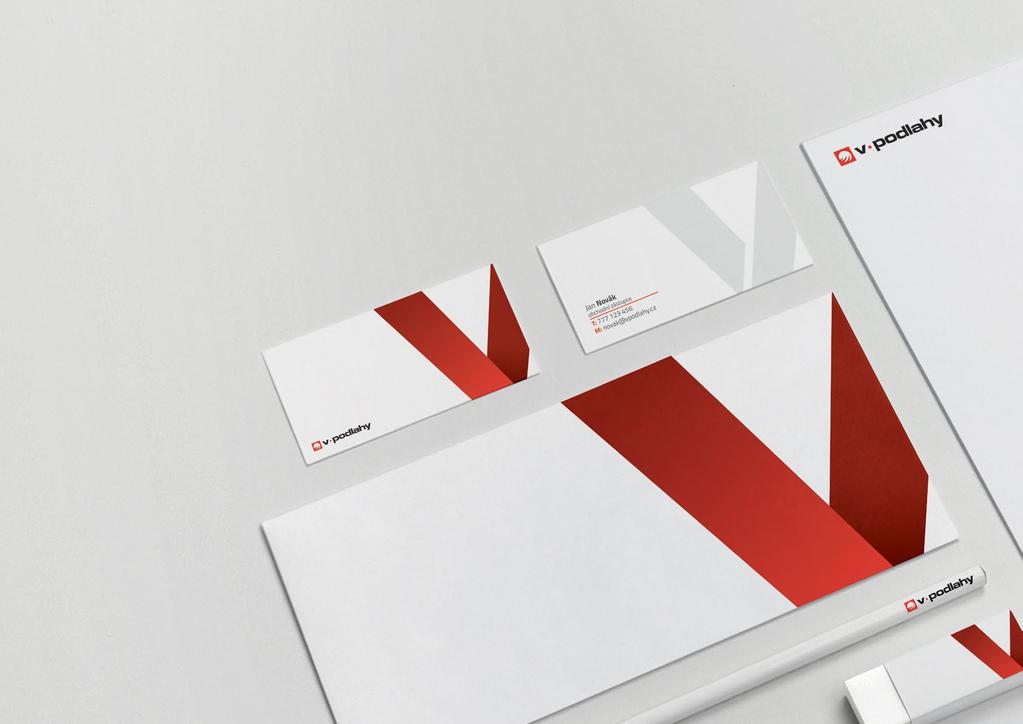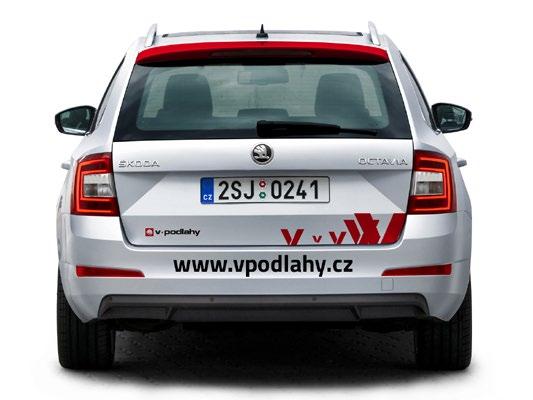
VIZUÁLNÍ STYL. Jednotícími prvky vizuálního stylu značky V-podlahy je ikona z loga, typografie, barevnost a pruhovanost.
3 VIZUÁLNÍ STYL Jednotícími prvky vizuálního stylu značky V-podlahy je ikona z loga, typografie, barevnost a pruhovanost. Cílem vizuálního stylu je působit sjednoceně. Vytvořit u cílové skupiny myslovou vazbu na jednotící prvky, které si jednoduše spojí s názvem V-PODLAHY. Vizuální styl má vyjadřovat moderní a svěží přístup. Výběr financí a sdružování kreativců do komunity. Schopnost pomáhat projektům nejen výběrem financí. Vždy je nutné dodržovat všechny jednotící prvky a řídit se předpisy pro vizuální komunikaci, kterou tento manuál sepisuje, aby se značka dala snáz cílovou skupinou zapamatovat. 3
7 ÚVODNÍ SLOVO A SPECIFIKACE ZNAČKY Corporate design manuál společnosti V-PODLAHY, s.r.o. je základním prostředkem k vytvoření jednotného vizuálního stylu, který společnost profiluje a dostává ji do podvědomí klientům, obchodním partnerům a široké veřejnosti. Jedná se o plnohodnotný marketingový nástroj a je jedním z prostředků k dosažení strategických cílů společnosti. Je také nástrojem, který odlišuje od konkurence. Jednotný vizuální styl je vytvořen z názvu společnosti, logotypu, firemního písma a firemní barvy. Pro vytvoření jednotného vizuálního stylu je nutné řídit se pravidly pro používání těchto základních prostředků ve všech formách vnější i vnitřní komunikace společnosti. Působení firemního stylu není omezeno navenek, ale významným způsobem ovlivňuje i vnitřní chod společnosti. Doporučení či nařízení pro správné užívání logotypů Podobu a pravidla použití jednotného vizuálního stylu popisuje tento grafický manuál, který je nezaměnitelný, originálním a závazným návodem k používání. Grafický manuál je především návodem k používání prostředků jednotného vizuálního stylu pro následnou realizaci. Jeho přesné dodržování je ve vlastním zájmu společnosti. Je zakázáno používat samotný logotyp nebo název společnosti bez respektovaní jednotného vizuálního stylu společnosti. V tomto manuálu jsou uvedeny příklady zakázaných variant, které však nevyčerpávají všechny zakázané způsoby použití. Jsou zakázány rovněž všechny způsoby použití, které se odlišují od variant povolených a popsaných v tomto manuálu. Pro jakékoliv způsoby použití je nutno respektovat pravidla tohoto grafického manuálu tak, aby nebylo poškozeno dobré jméno společnosti V-PODLAHY, s.r.o. 7
9 Logotyp Základní varianta logotypu se používá jako název s ikonou vodorovně. Varianty logotypu Vodorovná varianta Svislá varianta Samotný piktogram lze použít jako značku. Manuál zakazuje deformaci logotypu, změnu barevnosti, přidávání efektů, natáčení do jiných poloh než horizontální, změnu písma a změnu poměrů velikostí. 9
11 ochranná zóna Do místa ochranné zóny nesmí přijít žádný prvek, který by narušoval čistotu logotypu. Ochranná zóna je definována výškou piktogramu. Nejmenší velikosti se využívají hlavně na potisky propagačních předmětů, tiskovin apod. Minimální velikosti neplatí pro použití v digitální distribuci (web). ochranná zóna Ochranná zóna je zejména užitečná na prostoru, kde se logo V-PODLAHY nachází vedle dalších společností. Důležitá je výborná čitelnost a nenarušování ostatních logotypů. Ochranné pásmo kodifikuje piktogram. Určuje tak vzdálenost od stran bílého vnitřního obdélníku. 10mm Nejmenší šířka samotné ikony je 10 mm. 57mm Nejmenší šířka samotného nápisu je 57 mm. Nejmenší šířka horizontální varianty názvu s ikonou je 69 mm. 11
13 Logotyp se používá buď na bílé (až velice světlé) podkladové ploše v červeno-černé variantě, nebo na čistě červeném podkladu v bílé variantě. Podklady není možné měnit. Na fotce a odlišných podkladových plochách (např. video) se může použít buď pouze název a nebo logo skládající se čistě z bílé barvy. Bílé anebo velice světlé pozadí. Maximálně do 10% šedi. 13
15 DEFINICE BAREV Pro tisk přímými barvami je zde definice v Pantone (C označuje lesklý papír, U označuje papír bez lesku). Pro soutiskové barvy ve stupnici CMYK, pro použití na monitoru v RGB, speciálně na internetu pak v HEXA kódu. Předepsanou barevnost je nutné dodržovat co nejpřesněji. C 0 M 100 Y 100 K 0 C 0 M 0 Y 0 K 100 R 236 G 14 B 38 R 35 G 31 B 32 HEX #ec0e26 HEX #231f20 PANTONE 485 C PANTONE Proc. Black C 0 M 0 Y 0 K 50 R 147 G 149 B 152 HEX # PANTONE Cool Gray 7 EC 15
17 ZÁKLADNÍ PÍSMO PRO GRAFICKÉ APLIKACE Typografie je jedním ze základních prvků vizuálního stylu. Základním písmem společnosti V-PODLAHY, s.r.o. je rodina písem Titillium. Toto moderní a nadčasové písmo bylo navrženo Accademia di Belle Arti di Urbino. Písmo Titillium je určeno pro grafické aplikace, pro kancelářské aplikace. 17
19 APLIKACE ZNAČKY Logotyp vždy aplikujeme do levého horního rohu (pokud je možno). V případě, že levý horní roh je obsazen jinou značkou či grafikou, použijeme levý spodní roh dokumentu. Odsazení vždy 1cm od okraje dokumentu. Levý horní roh dokumentu Levý spodní roh dokumentu 1 cm 1 cm 1 cm 1 cm 19
21 VZOR Doprovodný vzor, který lze používat jako doplněk. dekorativní vzor 21
23 VIZITKA Vizitky tvoří důležitou součást jednotného vizuálního stylu. Jejich podoba vychází z jednotné grafické úpravy, předepsané tímto manuálem. Vizitky se tisknou na bílý papír - křída matná, gramáž g/m 2. přední strana zadní strana 50 Jan Novák obchodní zástupce V-PODLAHY, s.r.o. Jiráskova Vsetín T: M: novak@vpodlahy.cz 90 SPECIFIKACE Velikost: 90 x 50 mm Materiál: ONM White 300 g/m 2 Povrchová úprava: Laminace 23
25 HLAVIČKOVÝ PAPÍR Hlavičkový papír slouží jako univerzální merkantilní tiskovina. Může se používat ve dvou variantách - kompletně předtištěný kvalitním digitálním nebo ofsetovým tiskem na bílý papír o minimální gramáži g/m 2 nebo vytvořený pomocí šablony kancelářské aplikace přímo v osobních počítačích pracovníků společnosti. T: M: vpodlahy@vpodlahy.cz 25
27 dárková papírová taška tričko s krátkým rukávem 27
29 pohled z boku pohled zezadu 29